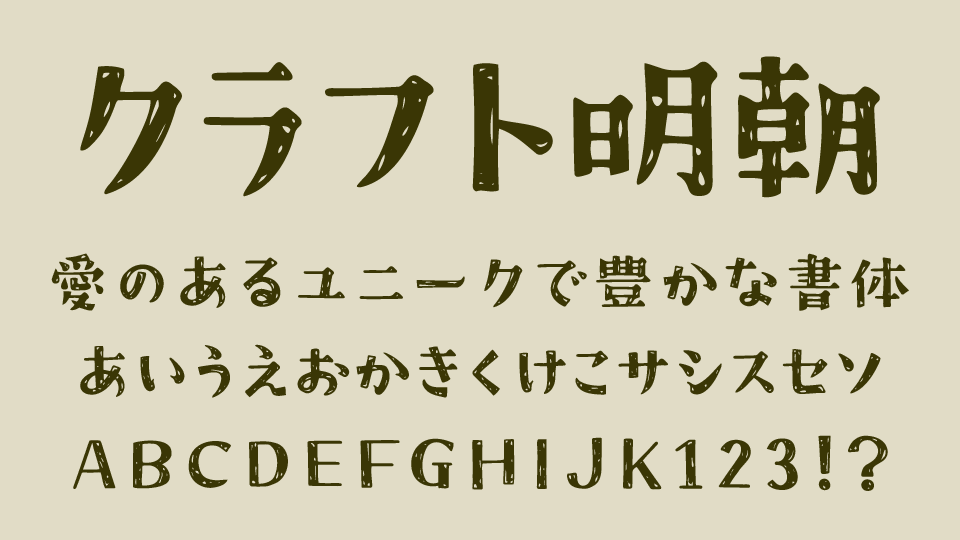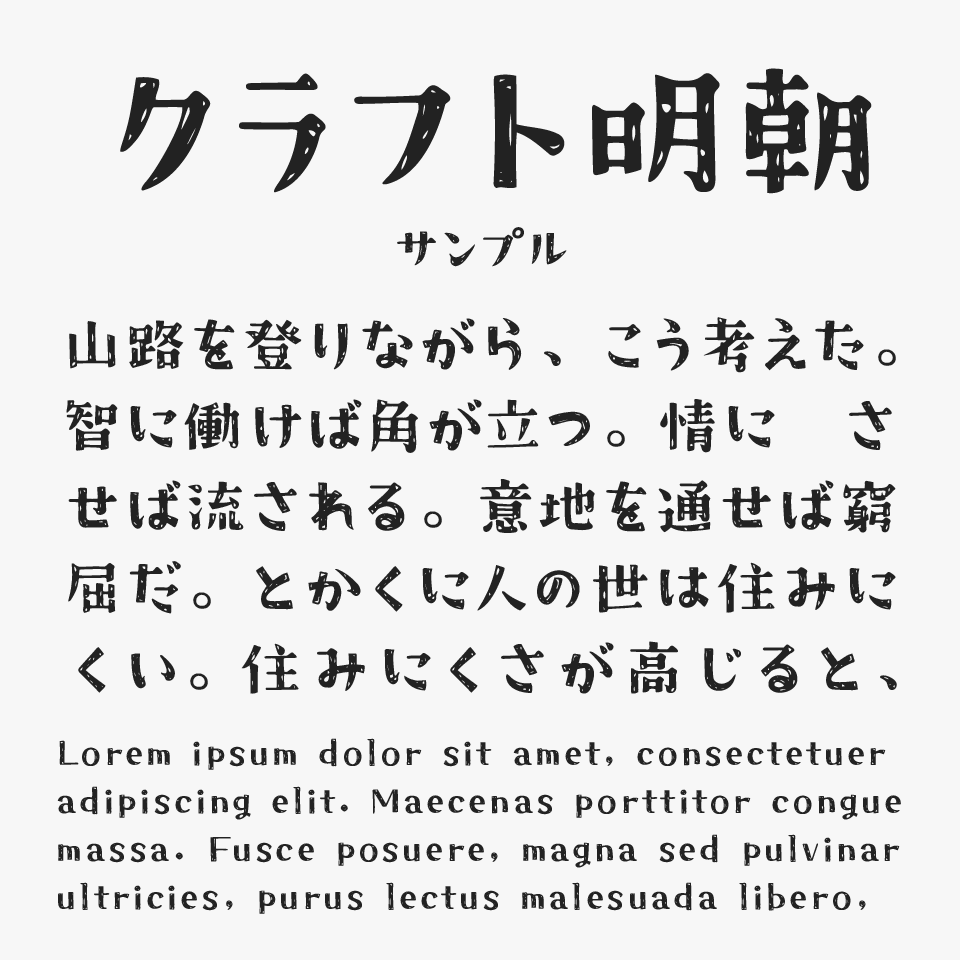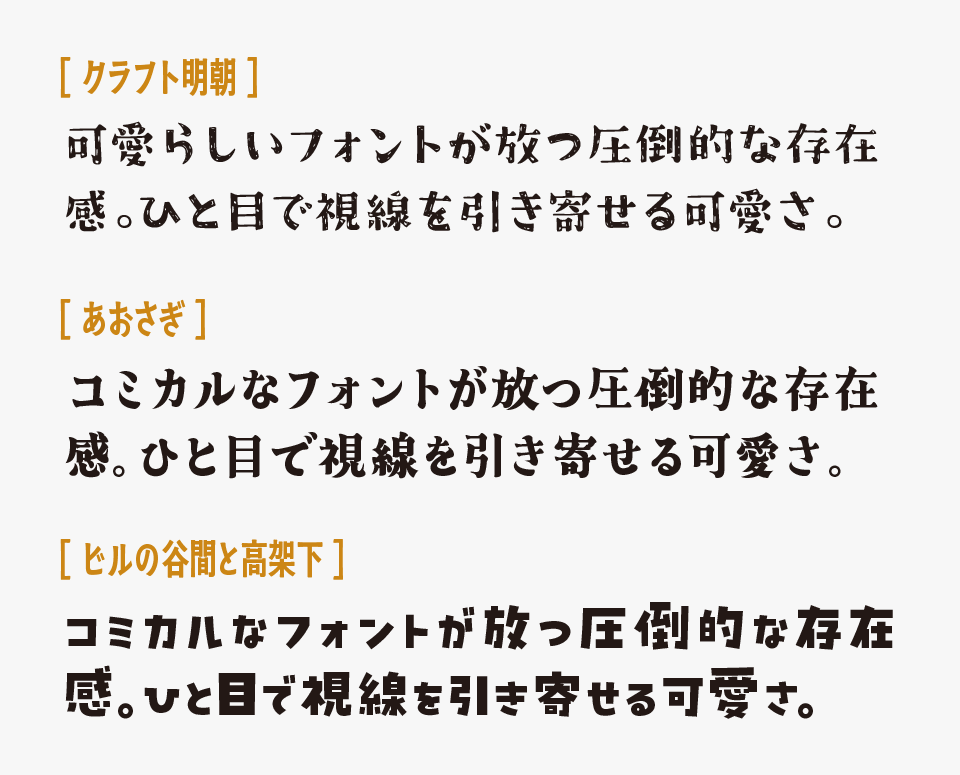
クラフト明朝
クラフト明朝フォントは、手書きでグシャグシャっと塗りつぶしたような、ラフなかすれ表現が特徴的なユニークなデザイン系明朝体フォントです。
ベースは明朝体になっているため、しっかりとした骨格や読みやすさを持ちながらも、表面には落書きのような遊び心がたっぷり詰め込まれています。整いすぎていないザラッとした質感がかわいらしく、見ているだけでも楽しくなるような雰囲気があります。
子供向けデザインやポップなタイトル、絵本風のビジュアル、ハンドメイド系の作品とも相性が良く、デザインに取り入れるだけで一気に親しみやすい空気感をつくってくれるフォントです。めちゃくちゃカワイイ…!
小さい文字でも、塗りつぶしたような質感が出ているのがとてもステキ。自分でこのような加工を作ろうと思うと少し大変ですが、フォントとして加工されているのはとても助かります。
ほかの“かわいい系”フォントと比較してみると、クラフト明朝フォントは、ポップな可愛らしさの中に少しクラシックな空気感が混ざっているところが特徴です。
明朝体ベースならではの落ち着きや上品さがほんのり残っているため、ただ子供っぽいだけではなく、どこかレトロで味わい深い雰囲気があります。(比較フォントは、あおさぎビルの谷間と高架下と比較しています。)